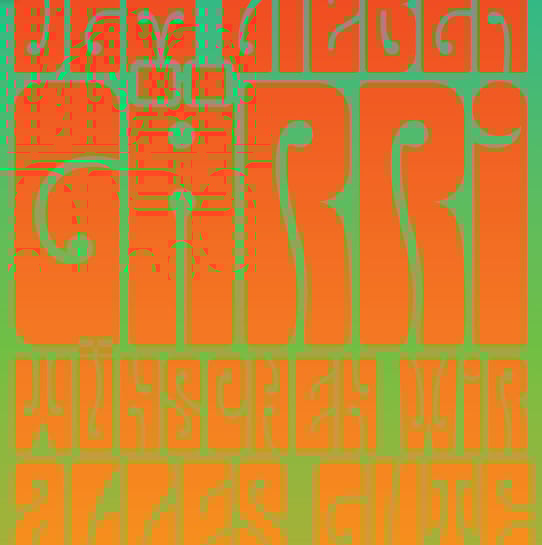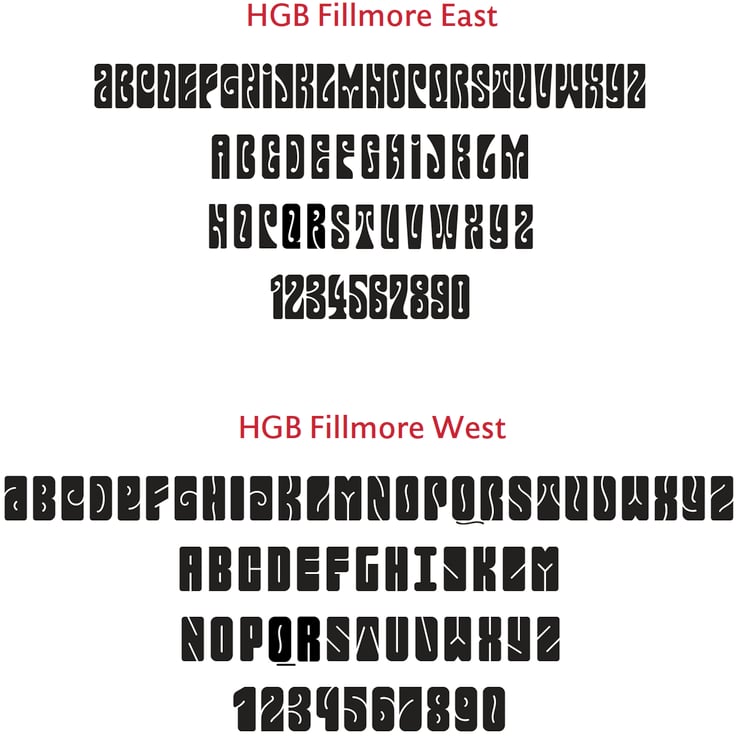
HGB Fillmore
Die typische Flower-Power-Schrift aus der Zeit um 1967/68, wie sie sehr oft auf psychedelischen Konzert-Plakaten zu sehen war, geht eigentlich auf eine Jugendstil-Schrift von Alfred Roller (1864–1935) aus Wien zurück (Wiener Sezession). Es gibt viele digitale Remakes dieser Schriftform, aber ich wollte das Formprinzip trotzdem noch einmal durchspielen. Ein herber Rückfall in die 60er-Jahre verbunden mit der Erkenntnis, die schon Wilhelm Busch formuliert hat: »Neue Gedanken sind nicht häufig, sag’ uns die alten nur geläufig.«